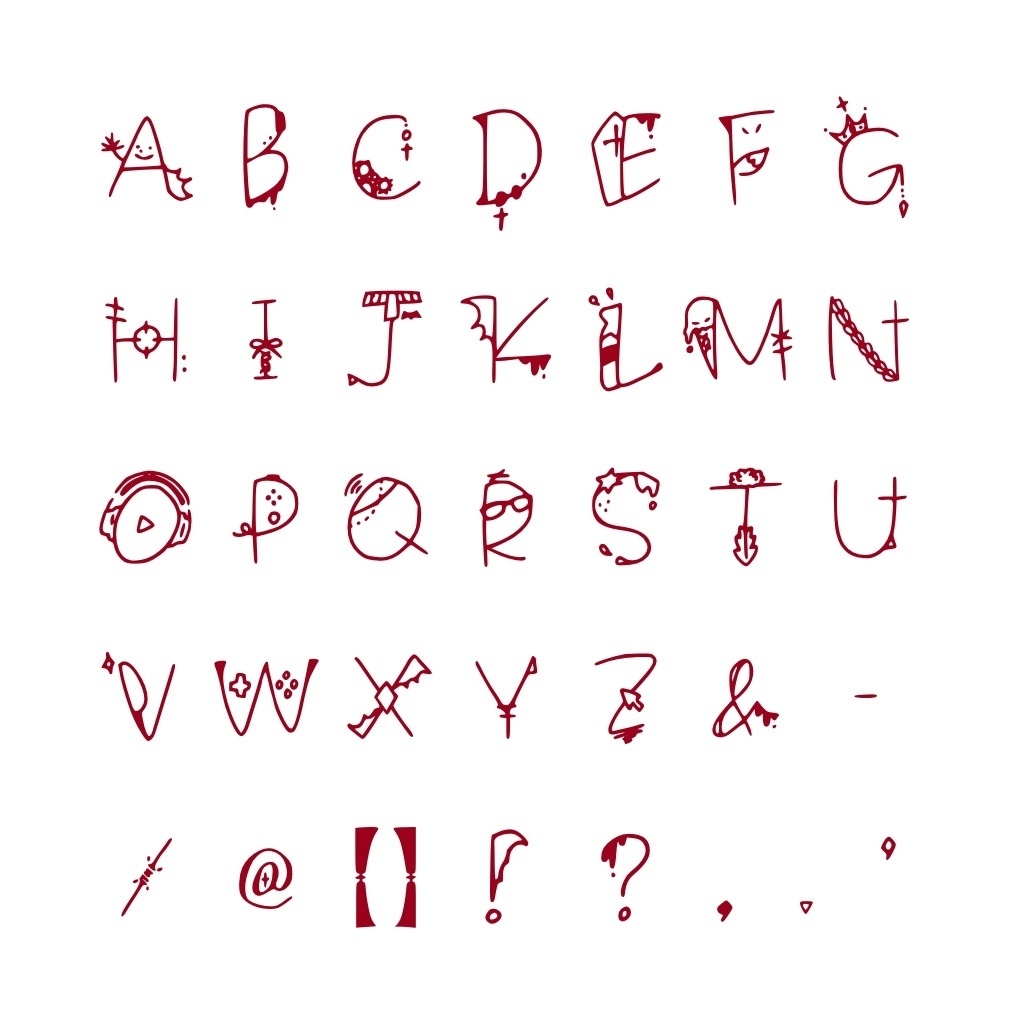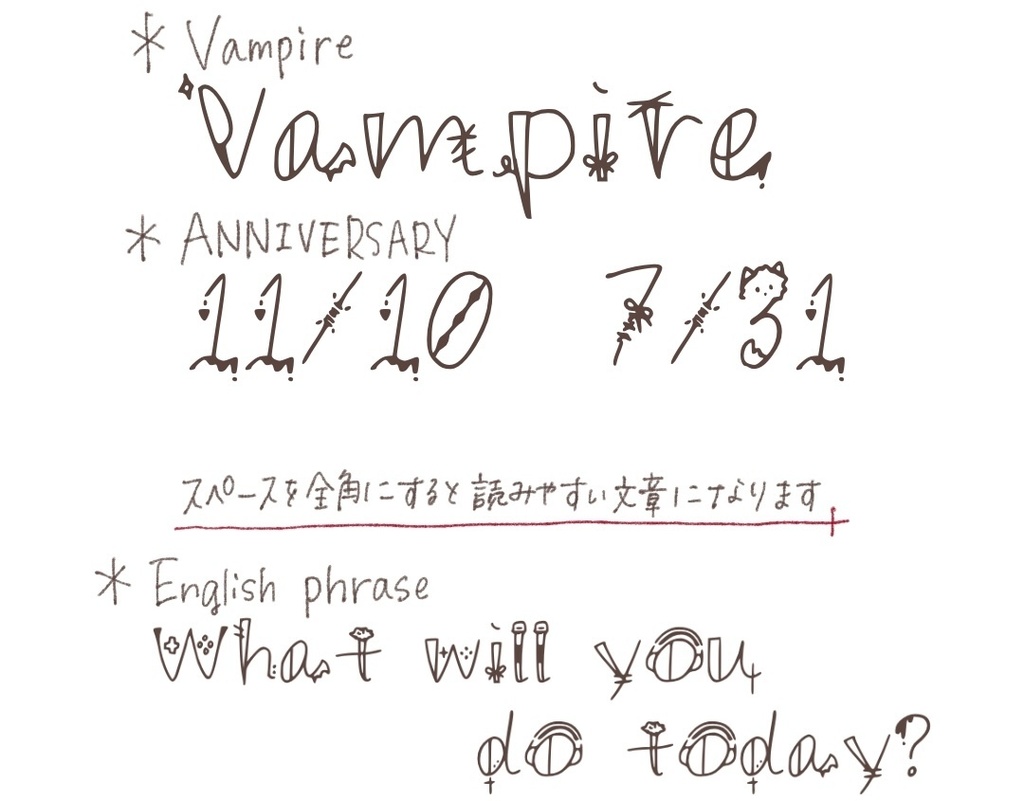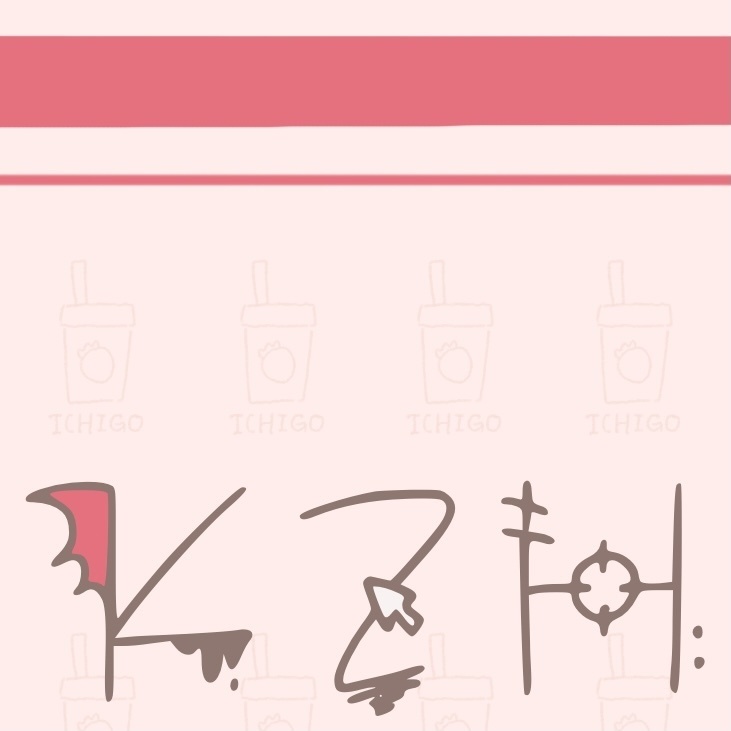
ひみフォント feat.葛葉【非公式】
にじさんじ所属『葛葉』をイメージした欧文フォント(非公式)。
ご購入、ご利用前に以下の内容を最後までお読みください。 にじさんじ所属『葛葉』をイメージした欧文フォント(非公式)。 キャラクターのモチーフを存分に詰め込んだオリジナルフォントです。 購入者様限定の解説と壁紙つき。 【商品内容】 ・フォントデータ(OTFデータ&TTFデータ)/収録文字:アルファベット大小・数字・記号少量 ・解説画像×2 ・おまけ壁紙(9:16) ご自由にお使いください!!IDの記載も自由です。トリミングも可。 【ご利用に際して】 *個人利用のみ可能です。同人も利用可。 *フォント名は『Himifont Feat Kuzuha』です。 *商業利用/フォントファイルの再配布及び複製・改変/フォントを使用した制作物の商標登録及び意匠登録/フォント自体がメインコンテンツとなる商品の販売、以上の行為は禁止です。 *利用報告・記載などは任意となっています。但し同人活動において販売物に使用した際は制作者(ひみ)の名前とTwitterIDを何らかの方法で必ず記載してください(どれだけ小さくても構いませんが必須とさせていただきます)。 *著作権は全て『ひみ』に帰属します。自作発言などはNGです。 *フォント利用に際し負った問題や損害の責任は負いかねます。 *本商品はファンアートの延長で作成したものです。二次創作物となりますので、本商品を使用した創作物に関しましてもANYCOLORの二次創作ガイドラインに従っていただきますようお願い致します。 *特に、ライバーさんに迷惑がかかる恐れのある使用は絶対に避けてください。 *ダウンロード時点で上記全てにご同意いただけたものとします。 その他本商品に関しまして気になることはお気軽にご質問ください。 2021/04/24 ひみ